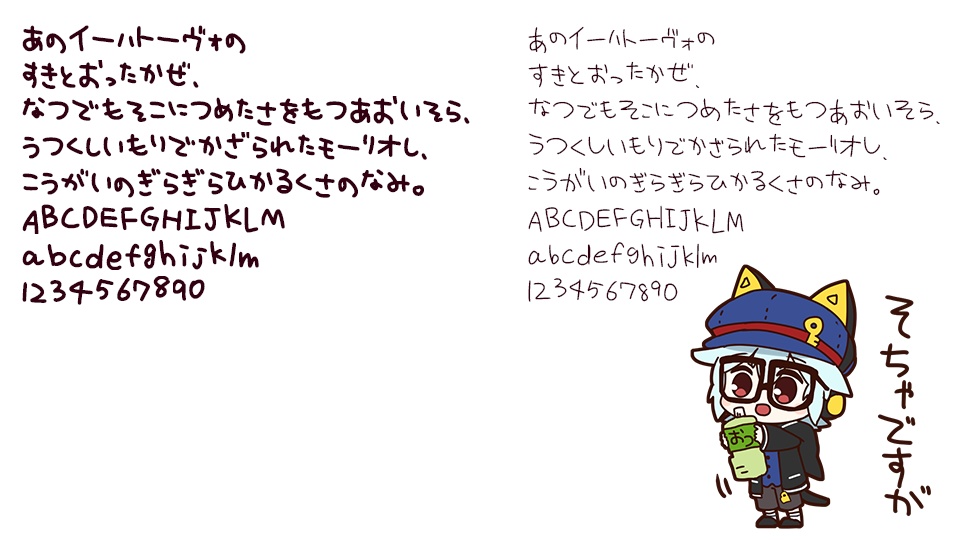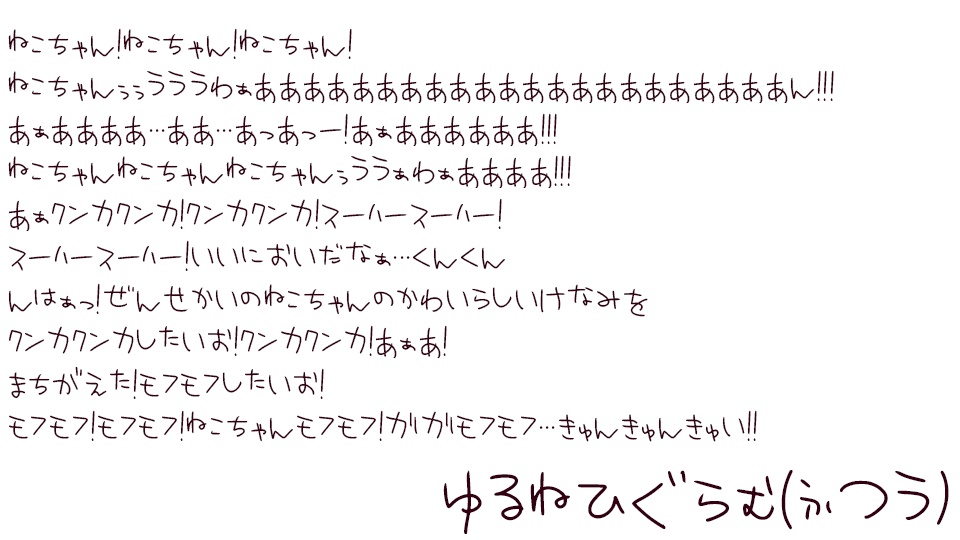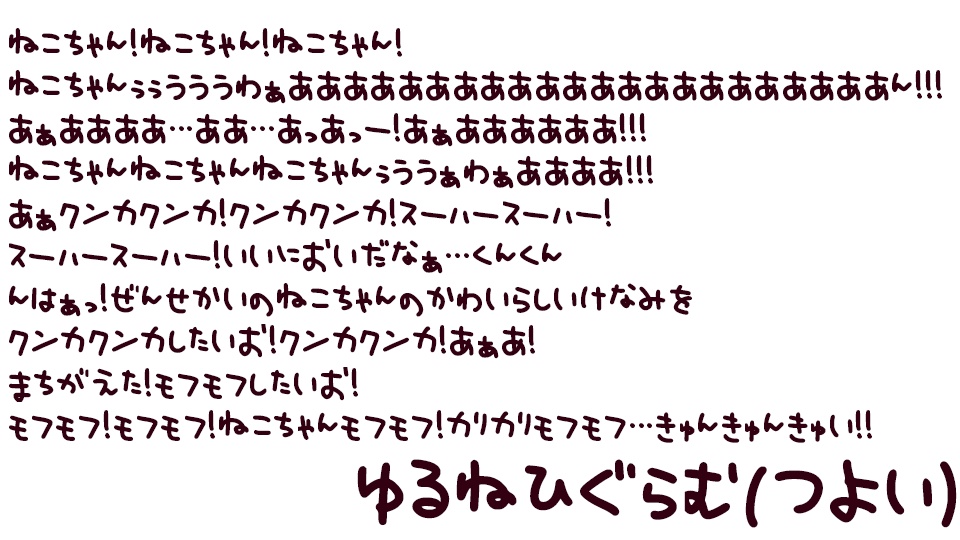
【無料】ゆるねひぐらむ【手書きフォント/商用利用可】
ゆるねひぐらむ TrueTypeフォント 制作日:2020/03/07 制作:緩音ヒグ/ひぐちかなめ 内容物: Yurunehigram(ふつうのほう) Yurunehigrambold(太いほう) ひらがな、カタカナ、数字、アルファベット、記号の一部が使えるはずです 権利関係: 著作権は放棄しません 二次配布禁止です ライブ配信などを含めた商用利用可能(報告不要です) ただし、フォントを使用したことによる責任は一切負いません その他なにかあればご一報ください 連絡先 BOOTHメッセージ https://highig07.booth.pm/ twitter@YuruneHig YouTubeチャンネル(よければ登録よろしくお願いします) https://www.youtube.com/c/YuruneHig